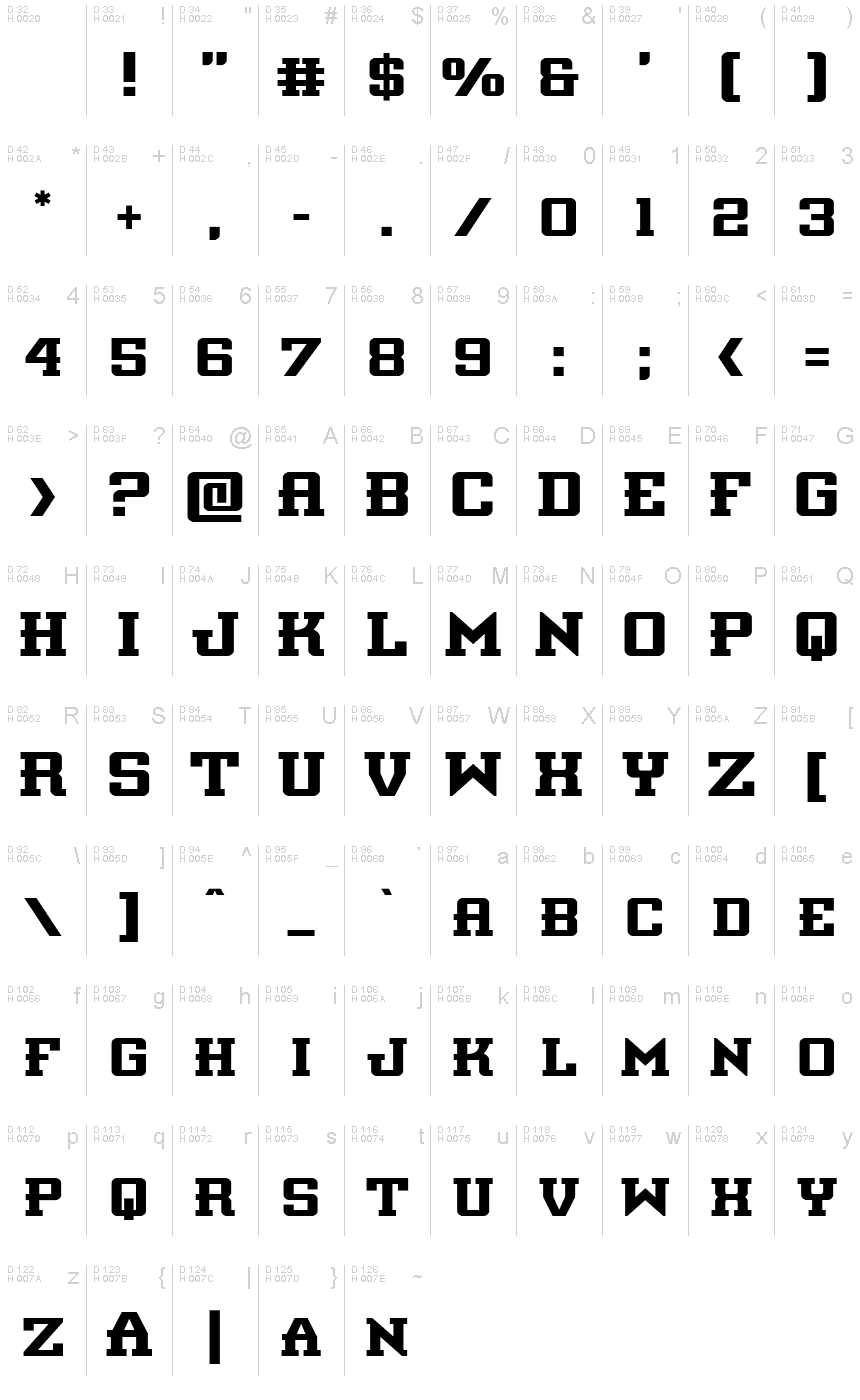
Interceptor von Iconian Fonts ist eine kostenlose Slab-Serif-Display-Schrift mit einem harten, modernen Varsity-Look. Die Buchstaben sind breit, quadratisch und markant, mit klobigen Serifen und gekappten Ecken – perfekt für Schilder, Team-Insignien oder eine raue Überschrift im Retro-Futurismus-Stil.
Das macht diese kostenlose Schrift zur idealen Wahl für Sport-Branding, Plakattitel, Gaming-Logos, Merchandise-Grafiken und Schlagzeilen, bei denen es auf kompakte Kraft statt Finesse ankommt. Sie funktioniert auch hervorragend für Titelkarten und Monogramme, da der blockartige Rhythmus kurze Wörter kompakt und zielgerichtet wirken lässt.